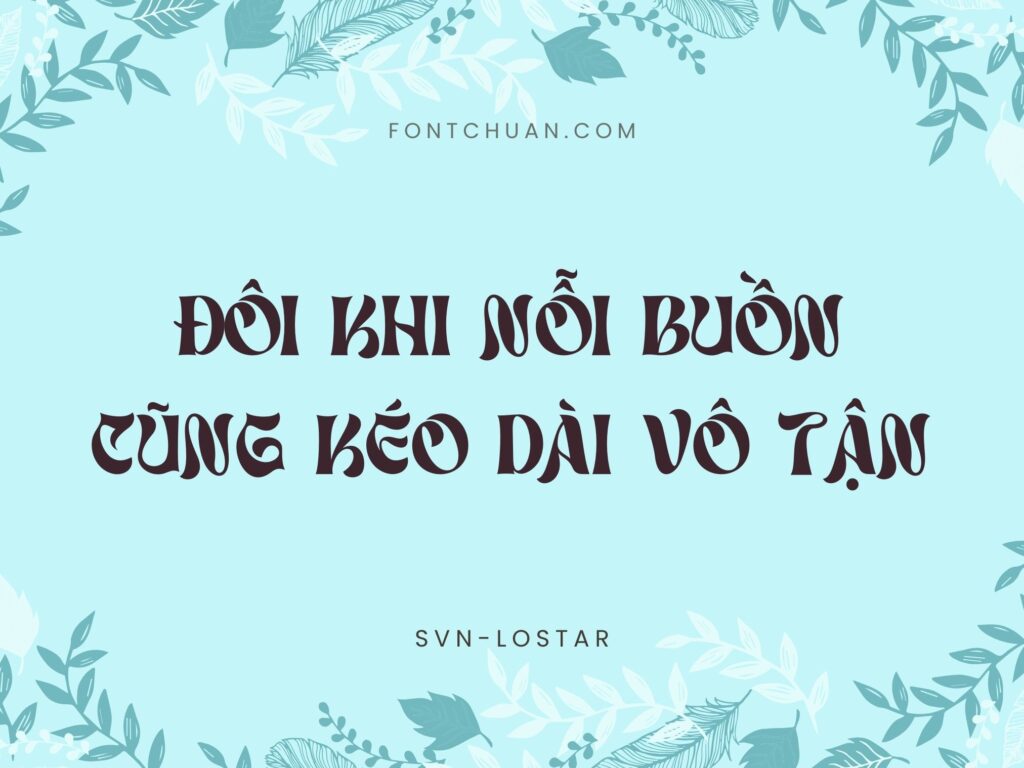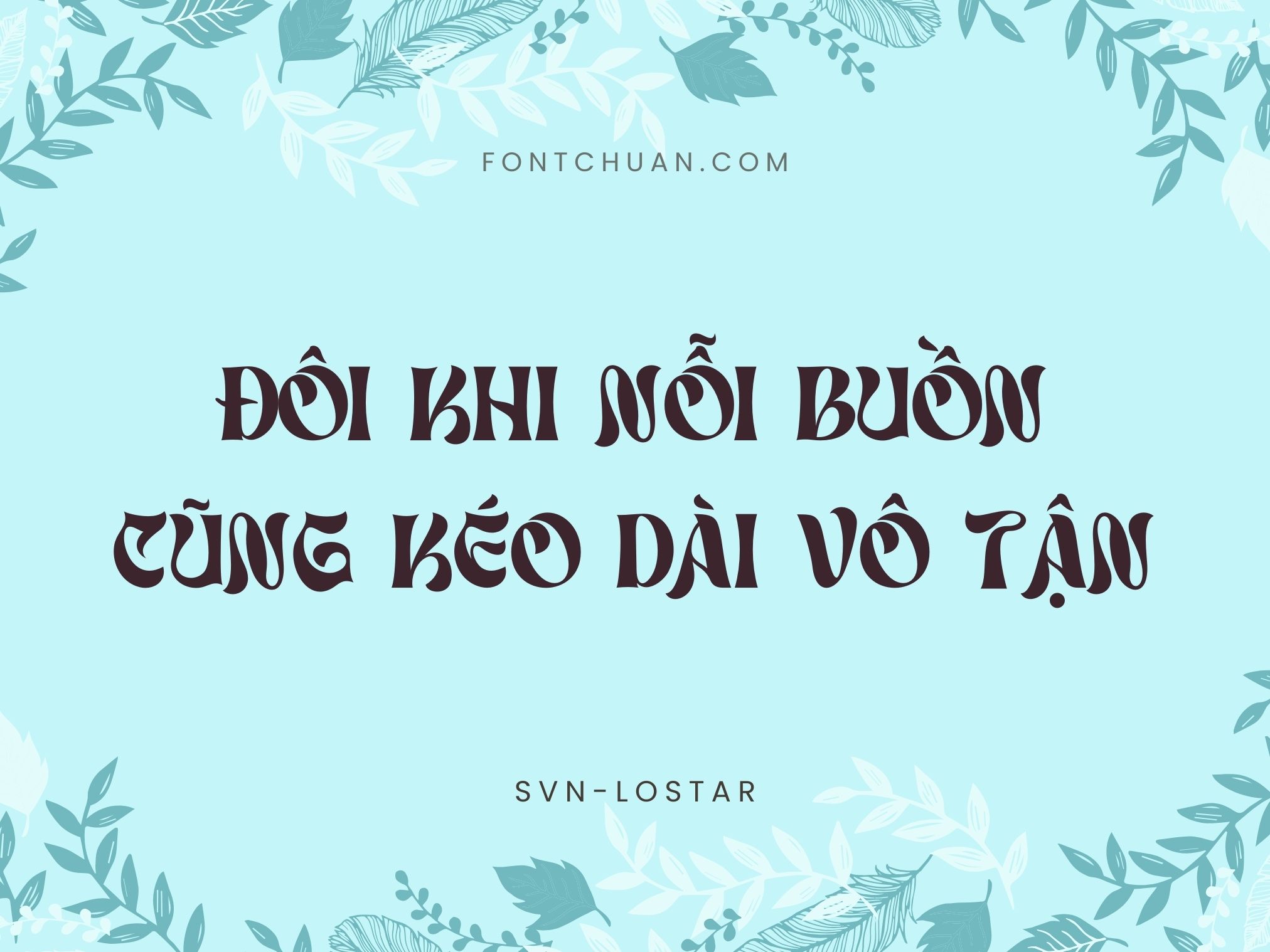
Font SVN Lostar Việt Hóa
Tác giả Font: Riyadh Rahman
Font SVN Lostar là phiên bản Việt hóa của kiểu chữ Lostar, được thực hiện bởi STYLEno.1 Fonts. Lostar là một kiểu chữ trang trí hiện đại với các đường nét độc đáo và đậm nét, tạo nên sự nổi bật trong thiết kế. Font này bao gồm các ký tự chữ hoa, chữ số, dấu câu và các ligature đặc biệt, hỗ trợ đa ngôn ngữ. Với thiết kế đặc trưng, Lostar phù hợp cho nhiều mục đích sử dụng như thiết kế tiêu đề, logo, poster, bao bì sản phẩm và các ấn phẩm truyền thông.
SVN Lostar lý tưởng cho các dự án thiết kế yêu cầu sự hiện đại và nổi bật, như thiết kế tiêu đề, logo thương hiệu và các ấn phẩm truyền thông. Các ngành nghề như quảng cáo, giáo dục và công nghệ có thể tận dụng font này để tạo điểm nhấn trong thiết kế. Ngoài ra, font cũng thích hợp cho các sự kiện như Tết, Giáng sinh, Halloween và các lễ hội khác.